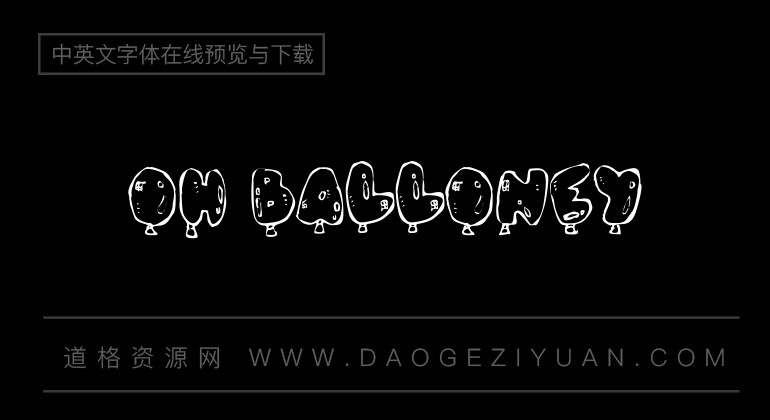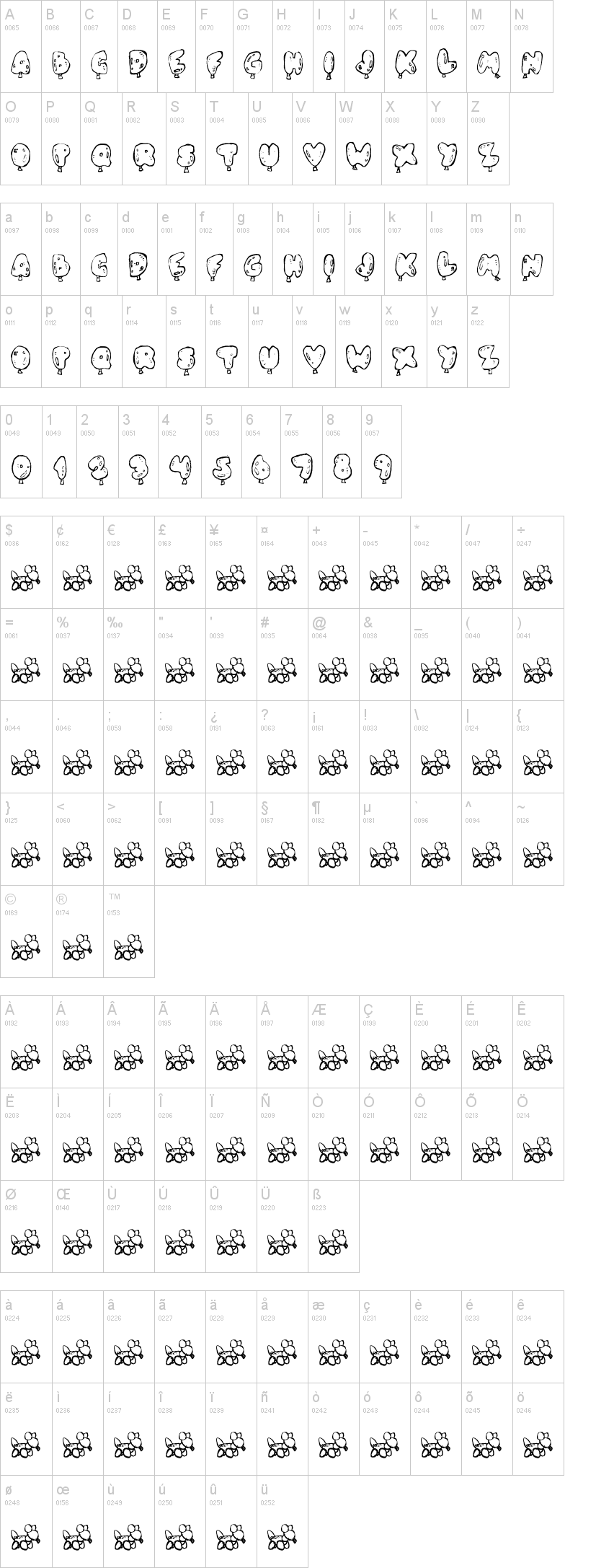
Oh Balloney
吗? Oh Balloney 是一款可爱的手写字体,由比利时设计师Jeroen van Eerden创作。它具有温暖的外观,细节丰富,拥有清晰的轮廓,可以用于给文字增添活力和可爱的气息。它拥有几种不同的重量,可以满足不同的设计需求。Oh Balloney 字体可以用于创建海报、海报、标志、标题、T恤、卡片等,也可以用于网页设计。
Oh Balloney是一款非常不错的手写艺术字体,具有很好的视觉感,适合于文化类的宣传设计、商业类品牌的广告和产品包装设计以及个性化文字排版等较多场景。
Oh Balloney字符映射图